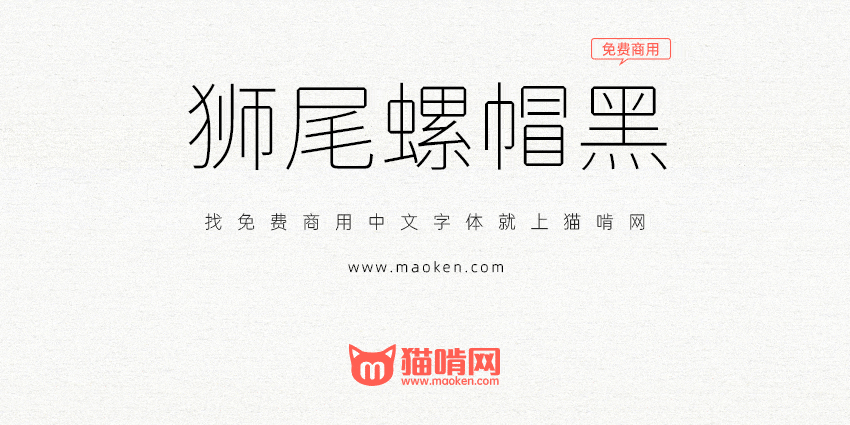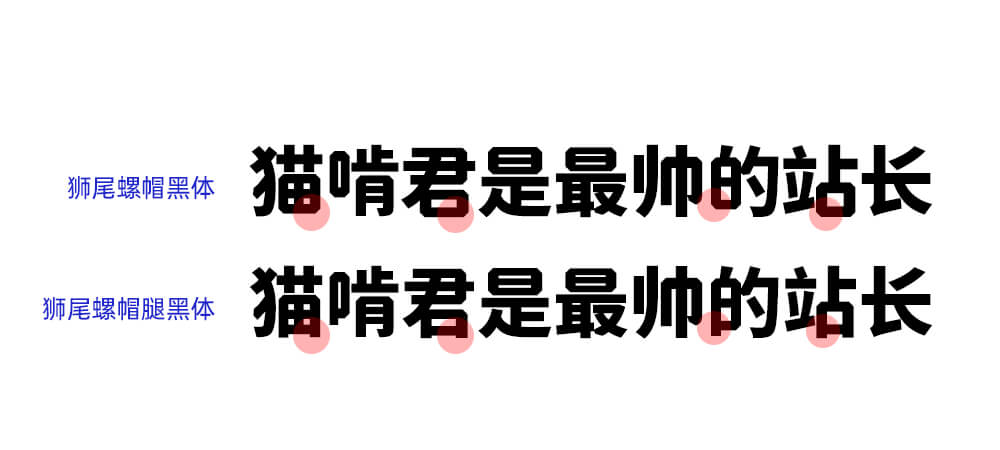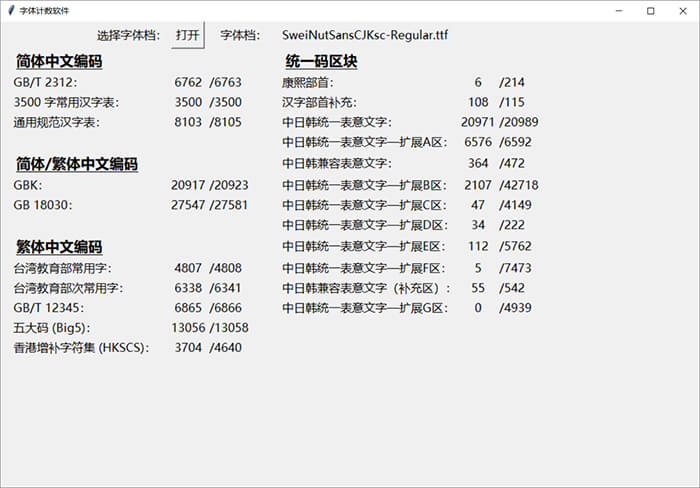
PS字体名:獅尾螺帽黑體/獅尾螺帽腿黑體 | 字体版本:Version 2.128(2020/10/18) 更新记录 |
字体作者:Max(中国大陆) | 字体字重:7个 |
狮尾螺帽黑体基于思源黑体增加斜角和拔脚改造,更加简明现代化的字体。支援简体中文、繁体中文、韩文与日文;欢迎大家自由应用、自由优化、自由改作!
狮尾螺帽黑体的特色是,“口”字的转角处增加一个斜角,外形有点像螺帽。
狮尾螺帽黑体和狮尾螺帽腿黑体差别在有没有拔脚,“拔脚”就是会有较少的笔画,例如移除“口”字的左右下角会多出的短线条。有拔脚的字会较圆,但是会造成有些字因直接去掉腿后左右不平衡、左右不对称的“悬空”问题。改使用“腿”系列字体就不会有这个问题。
这个字体改得蛮好看的,切角有点象折纸风格